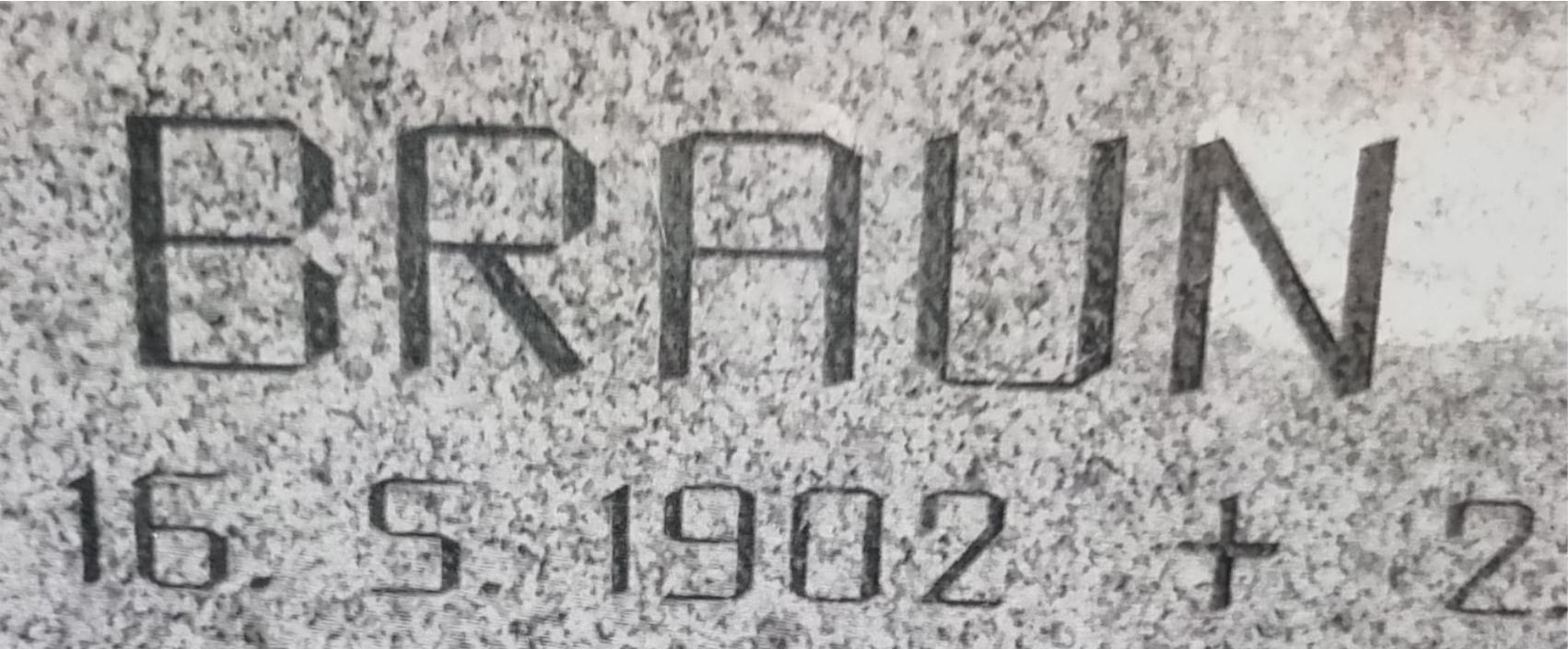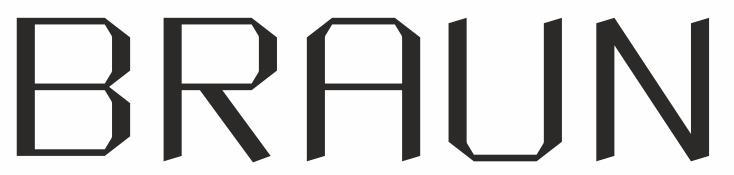
Schriftart für Grabstein
Ich bin auf der Suche nach einer Schriftart für einen Grabstein. Die einschlägigen Suchmaschinen spucken nichts aus.
Ich habe daher wenig Hoffnung was zu finden.
Vielleicht gibt es hier jemanden, der weiterhelfen kann.
Ich habe die Schrift mal nachgebaut und stelle auch das Originalbild ein.
Das weiß ich nicht, nach dem Geburtsjahr wird er schon älter sein.
Kann sein, dass es gar keine Computerschrift ist, sondern dass die handgefertigt wurde. Das hab ich mir auch schon gedacht....